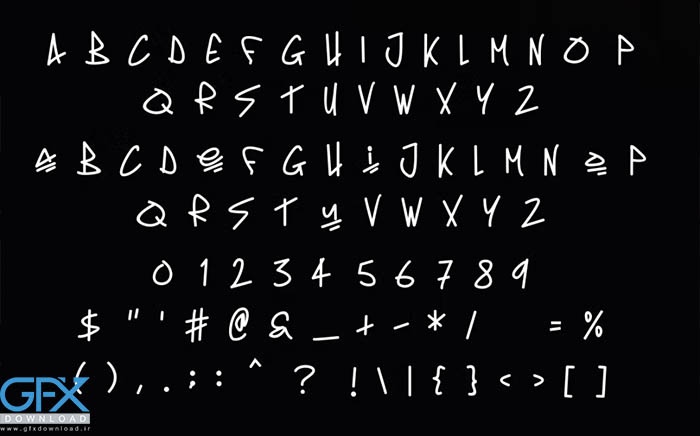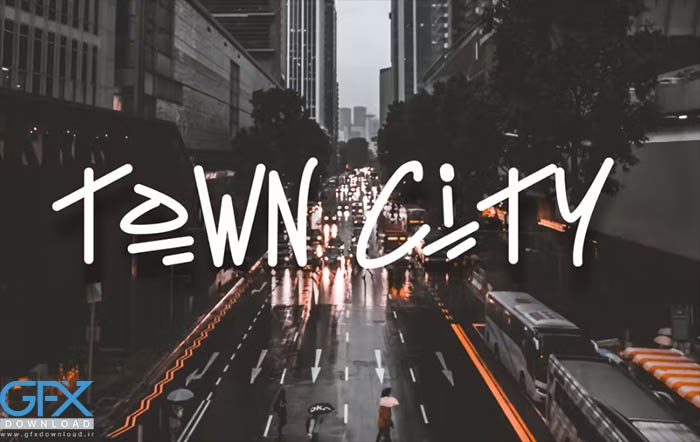
دانلود رایگان فونت Would
دانلود رایگان فونت انگلیسی Would
دانلود رایگان فونت Would یک فونت انگلیسی مدرن و معتبر است. مناسب برای نیازهای حرفه ای و برندینگ یک محصول. این فونت برای هر پروژه برندسازی مانند نقل قول، لوگو، هدر وبلاگ، پوستر، نواربندی، نامه، دعوت نامه، لوازم التحریر و غیره مناسب است. مناسب برای طیف گسترده ای از زمینه ها.